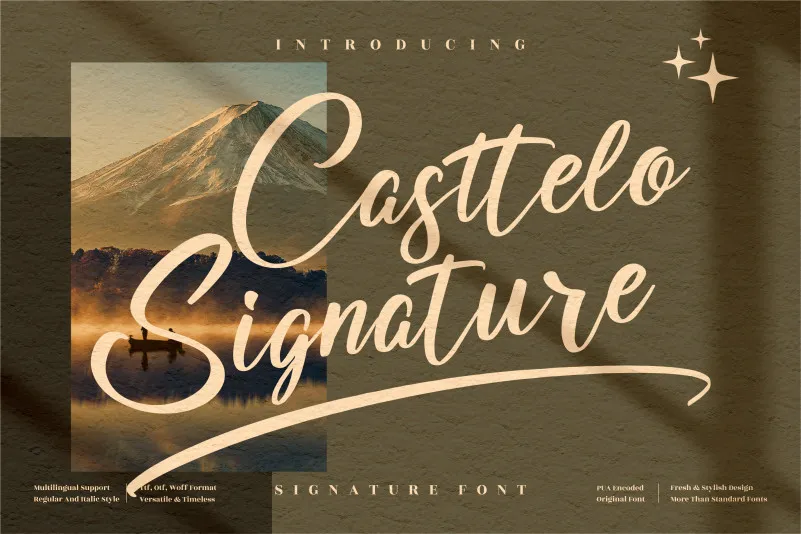
Casttelo Signature Font – Download Grátis
Esta fonte traz uma sensação incrivelmente elegante e fluida. Seu estilo desliza perfeitamente para cartões de agradecimento, cartas de casamento, frases inspiradoras ou cartões de boas-vindas, bem como para logotipos e cartões de visita onde se precisa dar um toque de escrita à mão. Sua natureza variável na base permite uma interação fluida entre linhas e espaçamentos, enquanto suas formas meticulosamente detalhadas (glyphs) são acompanhadas por alternativas de altíssimo nível, criando um conjunto perfeito para todos os projetos gráficos que buscam um toque autêntico. Ideal para qualquer design onde se deseja dar vida à sua tipografia com um toque delicado e sofisticado.